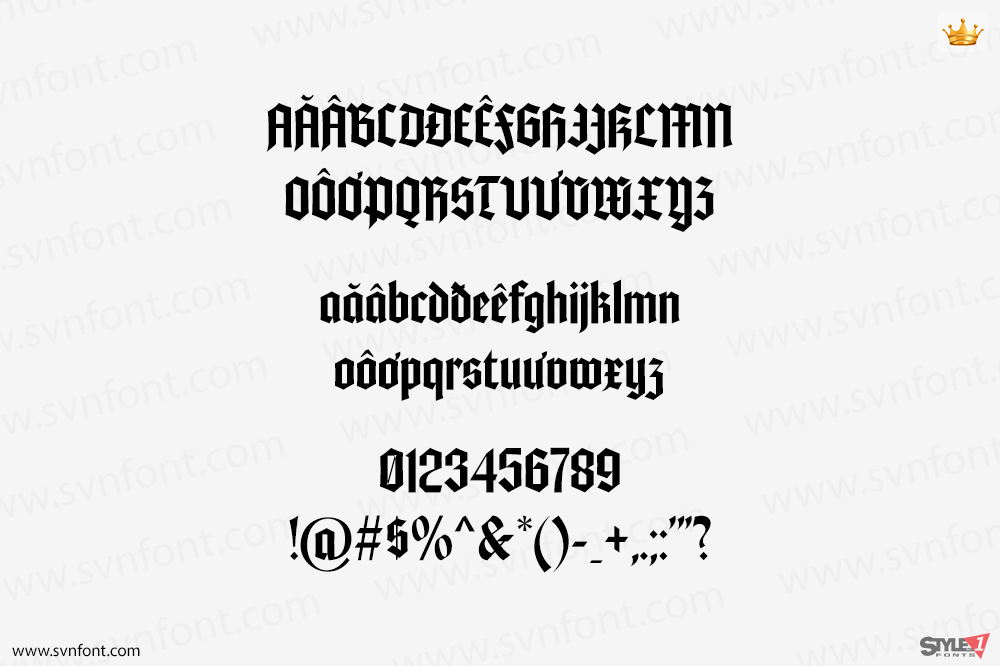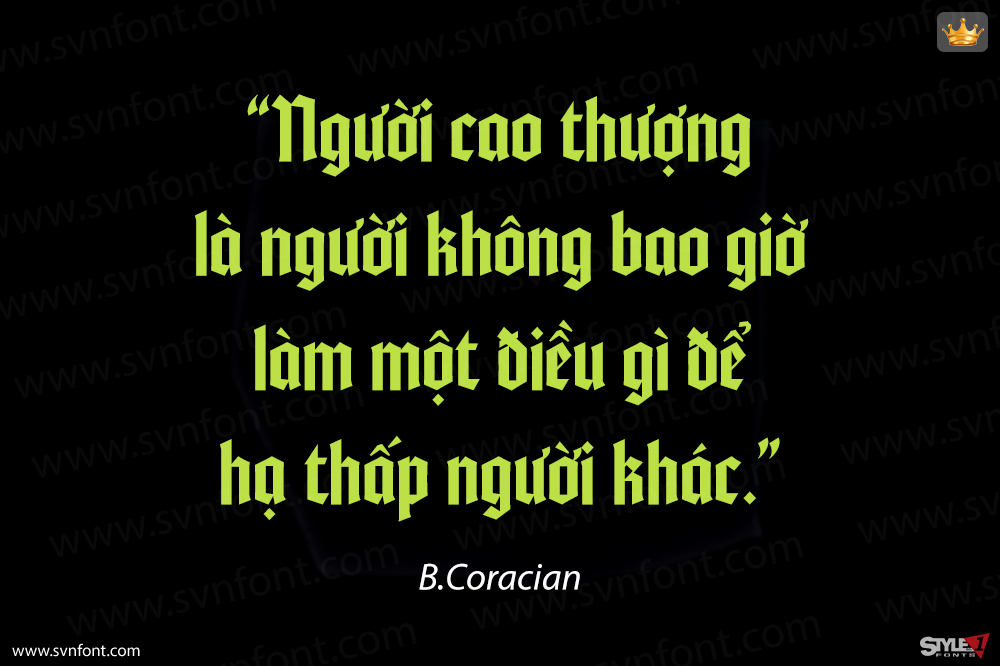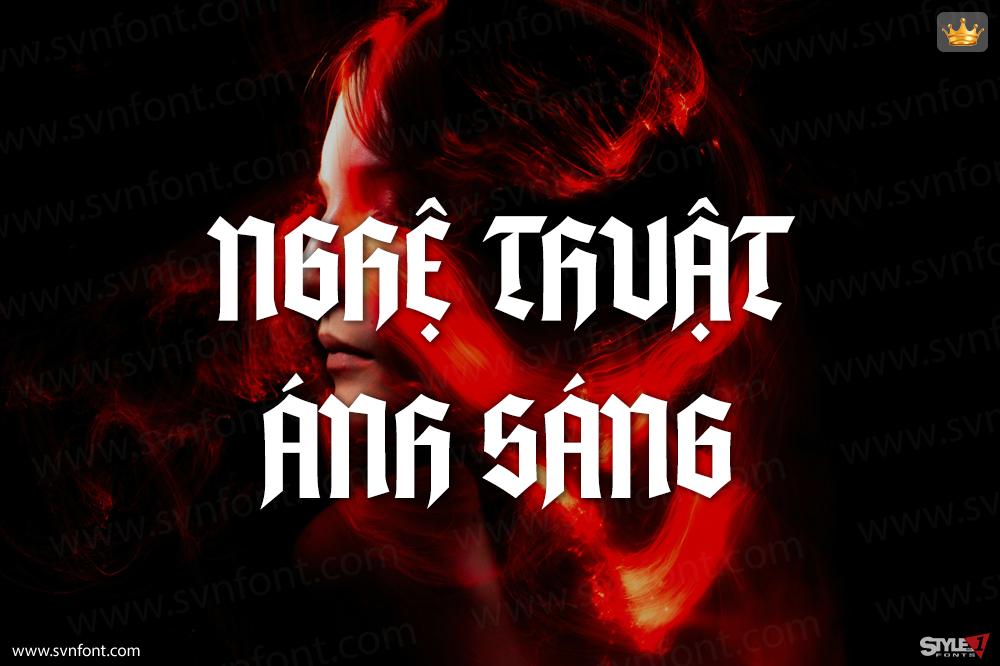
ED Smither là một phông chữ blackletter kiểu textura mang vẻ ngoài sạch sẽ và hiện đại. Thiết kế phông chữ này được lấy cảm hứng từ “Standartarte” năm 1934 của Schelter & Giesecke Leipzig, với một sự tái thiết kế làm cho các chữ cái trông hiện đại hơn. Phông chữ này cũng bao gồm các tính năng hỗ trợ như chữ ghép, ký tự thay thế và hỗ trợ đa ngôn ngữ.
Nhà thiết kế: Emyself Design